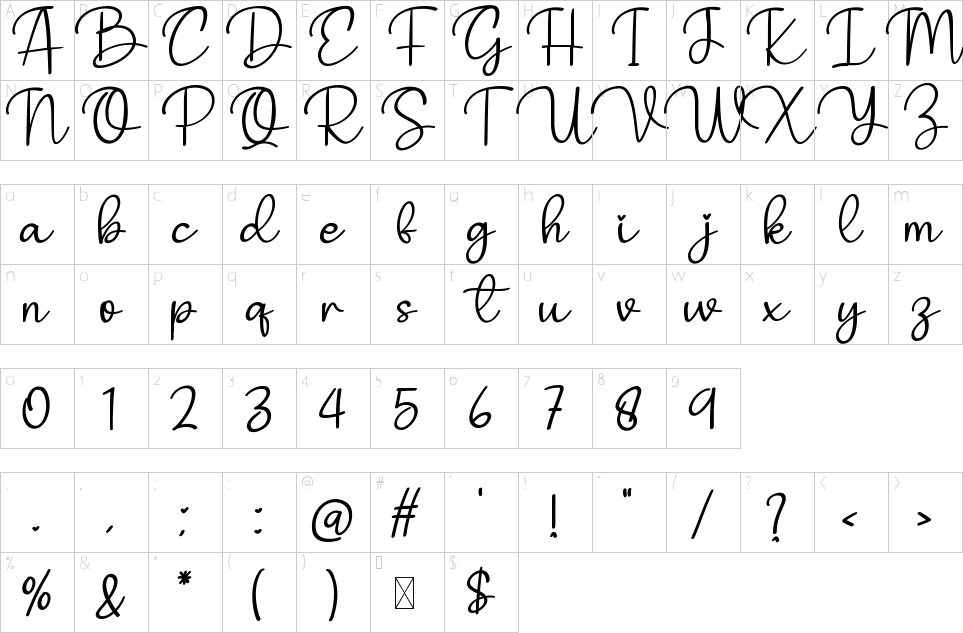
Angelic Font – Download Grátis
A fonte ‘Angelic Font’ é uma delicada e elegante escolha para qualquer projeto gráfico. Desenvolvida por scratchones, esta fonte possui um charme especial que a torna uma opção única para criações de alta qualidade. Seu design delicado e arrojado complementa perfeitamente designs de arte, ilustrações e até mesmo elementos de e-commerce. Com um estilo único que chama atenção sem ser intrusivo, a Angelic Font é uma escolha ideal para aqueles que desejam um toque especial em suas criações digitais. Recomendada para uso em projetos pessoais e corporativos, este ‘grátis’ para Windows e Mac tem sido baixado 1.720 vezes, demonstrando sua popularidade e qualidade. Instale-a hoje e experimente a diferença que ela pode fazer em seu trabalho.